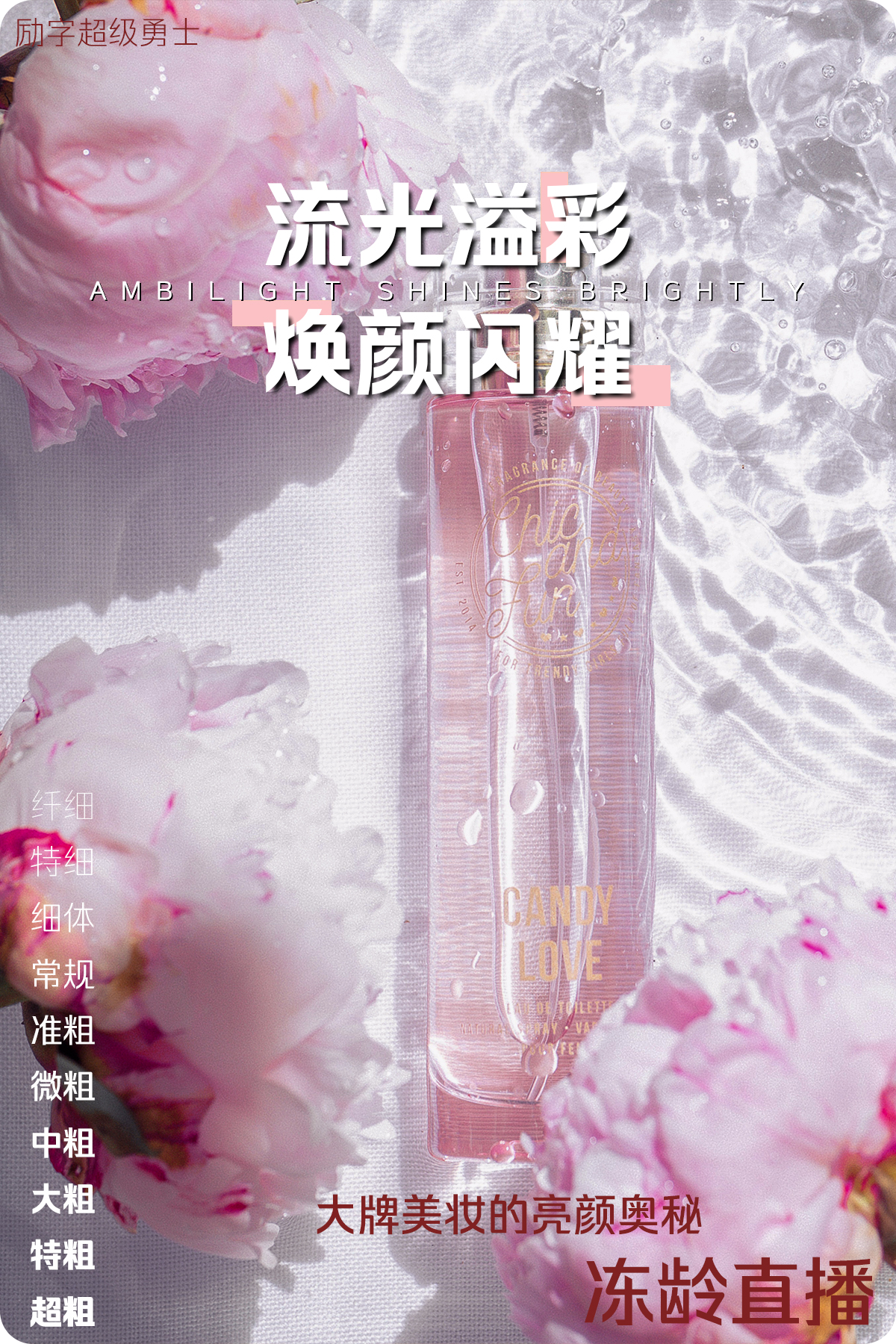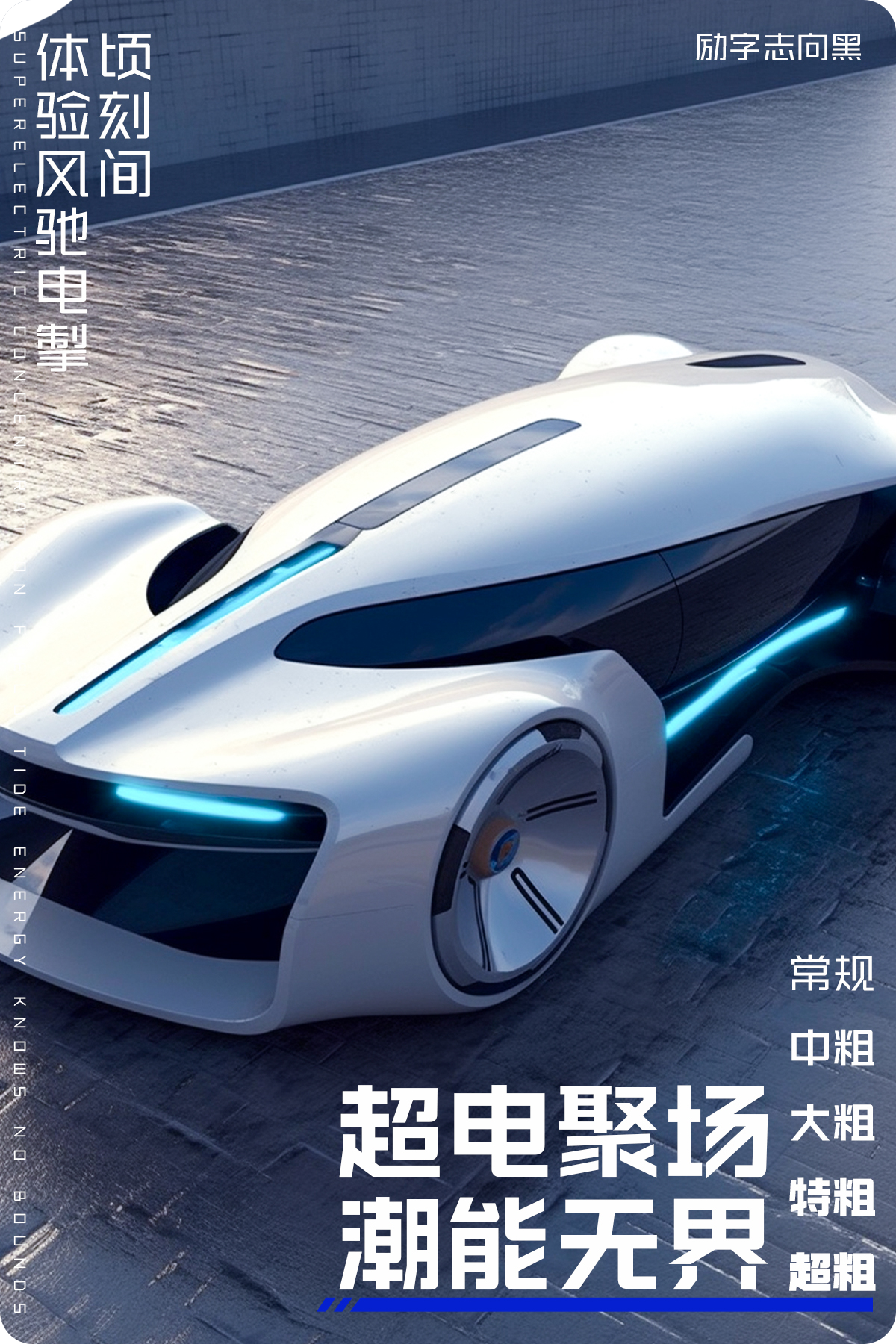
字体LOGO设计 | 品牌LOGO设计趋向,为什么现在品牌都有定制LOGO
LOGO在世界范围内共分为五大类型(图文徽章标志、文字徽章标志、文图结合标志、文字标志和独立图形标志),品牌应依据自身的名称呼叫特点、行业共性、面向群体、不同的发展阶段以及应用场景选择适合自己的类型,类型的选择将决定设计的发展方向并帮助品牌达到事半功倍的累积效应。
今几年,伴随字体版权的规范化及中国市场的强势崛起,品牌LOGO的选择从原来的西文进化为中文,中文LOGO更具识别性与可读性。励字造梦共创字库精选2款字体LOGO !
智能汽车类LOGO字体
励字志向黑简,以粗细均匀的直线笔画诠释智能汽车的极简数控,
笔画起止端平切、直切的设计,
更契合智能屏显系统识别读取,
折笔处采用外圆角设计,彰显流畅丝滑的人车合一体验。
美妆类LOGO字体
励字超级勇士简 ,起笔处倾斜和平直设计灵活处理,灵动妆效跃然纸上,
折角笔画由外圆角与方角有序组合,正如美妆叠加时的完美搭配,
撇捺弧度饱满,流畅度、亲肤感满分。